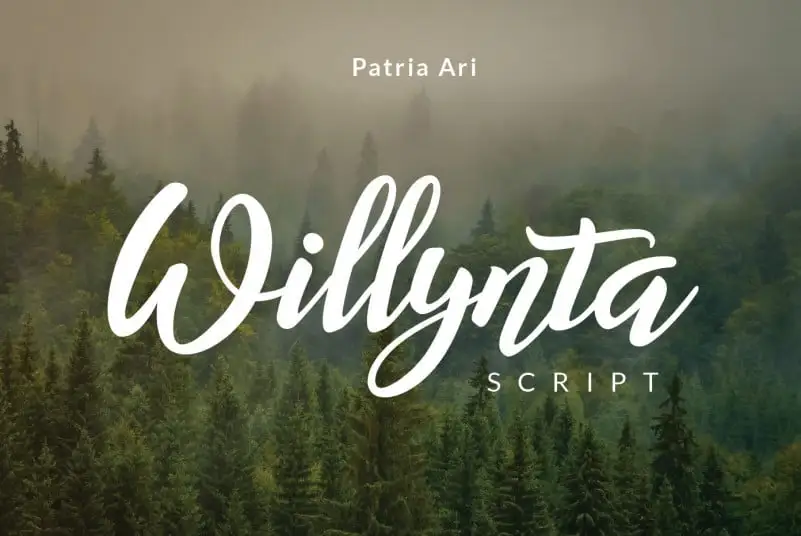
Willynta Script Font – Fonte Grátis
Willynta Script Font
Descobrimos uma nova adição para nosso catálogo de Fonts, chamada Willynta Script Font. Esta elegante tipografia script é feita à mão e traz um toque divertido e único ao estilo tradicional. Perfeita para quem busca uma fonte versátil para headlines, logotipos, roupas, convites, marcações, embalagens, e até mesmo anúncios, Willynta Script tem tudo que você precisa para dar um toque especial a qualquer projeto. Ideal para personalizar o seu design de maneira única, a Willynta Script é uma adição incrível aos designers gráficos. Sua escrita natural é ideal para estilos criativos e modernos, garantindo uma mistura perfeita entre elegância e diversão. Seja você um designer de moda ou artista visual, essa fonte vai ser uma excelente escolha para tornar seus trabalhos ainda mais atraentes e pessoais. Com o Designer Patria Ari Typestudio, Willynta Script se destaca por sua capacidade única de dar vida aos textos com seu charme delicado. Seja você que está buscando um novo elemento para suas criações digitais ou presenciais, não hesite em explorar a versão completa da Willynta Script – certamente irá impactar positivamente qualquer projeto gráfico em que ela for aplicada.